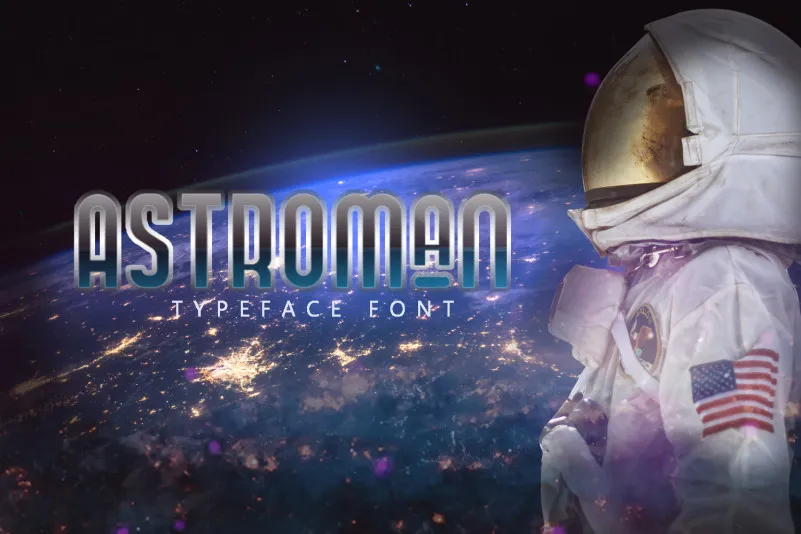
Astroman é uma fonte de estilo sans serif que traz um tom moderno e elegante para qualquer projeto. Inspirada nas linhas geométricas e na simplicidade dos estilos de fontes mais simples, Astroman oferece uma versatilidade impressionante que vai do profissional ao casual, adaptando-se a diversas aplicações. Seja em um site pessoal ou no design gráfico, ela traz uma dose extra de estilo sem comprometer a legibilidade. Através de sua simplicidade e precisão, Astroman é uma ótima escolha para quem busca uma fonte de qualidade que não seja apenas funcional, mas também capaz de destacar seu trabalho de design. Para usuários amantes do bom gosto ou simplesmente querendo experimentar um novo estilo, não há dúvida de que Astroman é definitivamente algo a ser considerado em sua coleção de recursos gráficos. A Fonte foi criada pelo designer mhdafifersya e está disponível gratuitamente para download através da fontbundles.net/mevrickstudio/295491-astroman-typeface/.